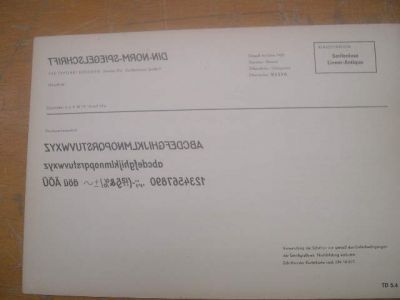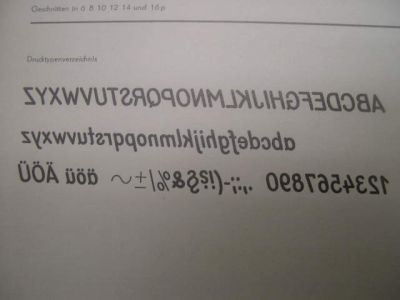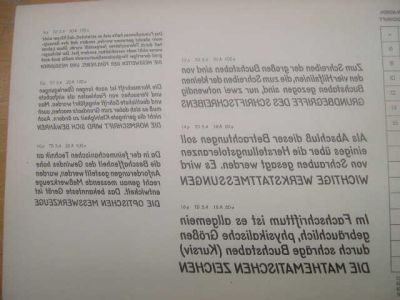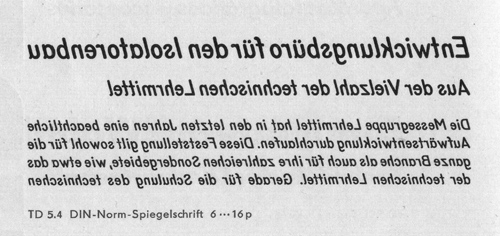
DIN Spiegelschrift bei Schelter & Gisecke
Albert-Jan Pool hat mich per E-Mail um nähere Infos zu dem Wiki-Artikel über Typoart gebeten. Dort war als Ursprung für die DIN Norm Spiegelschrift »Schelter & Gisecke 1925« verzeichnet. Weiß jemand etwas darüber oder hat vielleicht sogar die betreffene Probe?
Ich habe eine Typokartei von TypoArt mit einem vollständigen Zeichensatz und Textproben.
Was braucht Ihr denn?
Gedruckt ist dieses Muster auf recht holzhaltigem Papier und nicht in allerbester Qualität.
also in der "gedrängten probe" von schelter & giesecke die ich habe
war sie nicht. allerdings habe ich ebenfalls ein schriftmuster von typoart
gefunden. ein blatt, A5, in 6 verschieden schriftgrößen.
kein alphabet, keine angabe zum designer, nur blindtext.